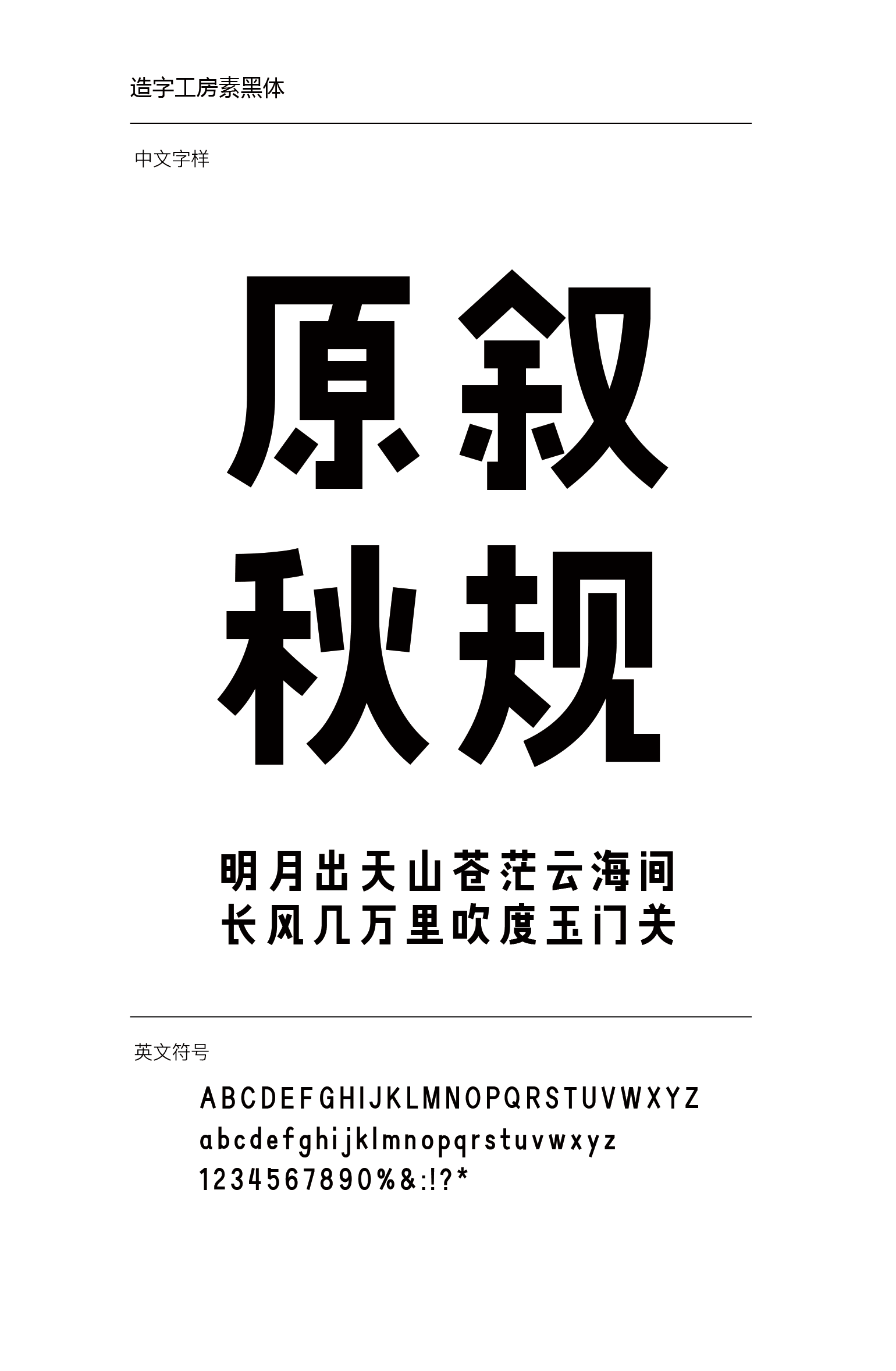
造字工房素黑体设计说明
造字工房素黑体字型设计中宫内敛,结构严谨,运笔简洁,灵动秀气。笔画挺劲有力,瘦逸犀利,刚柔结合,独具个性。结体整齐平正,婉转巧妙,平和畅达,赏心悦目。字形设计视觉重心的提高,令其整体造型舒展优雅,明快有力,法意兼备,隐有民国风骨兼具人文情怀。适用于大标题及个性品牌设计推广等环境。本字体为简体字库,采用OpenType/CID格式,Adobe-GB1-5编码。基于中华人民共和国GB2312-80字符集标准,另按需添加101个汉字。共收容字数6864CJK汉字,ASCII常用字符100个。